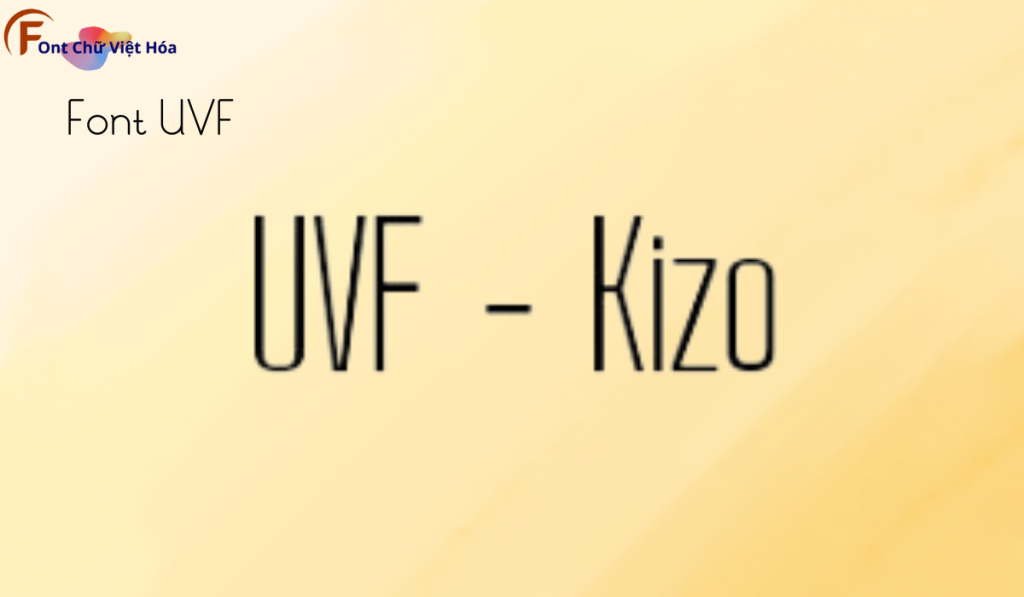
Font UVF – Kizo Việt Hóa
Font UVF-Kizo Việt Hóa
Bộ Font: UVF
Phân loại: Độc đáo
UVF-Kizo Việt Hóa là font không chân với các đường nét cá tính và độc đáo, thuộc bộ font UVF. Font này được thiết kế nhằm mục tiêu tạo ra sự rõ ràng và dễ đọc, đặc biệt phù hợp cho các thiết kế như poster, logo, và tiêu đề. Đặc điểm hình dạng của UVF-Kizo là các đường nét đậm và tỷ lệ chữ cân đối, giúp tối ưu hóa không gian và tạo ấn tượng thị giác mạnh mẽ. Font này cũng đã được Việt hóa, mang đến sự linh hoạt và tiện dụng cho các dự án thiết kế bằng tiếng Việt, giúp người dùng dễ dàng tiếp cận và sử dụng.